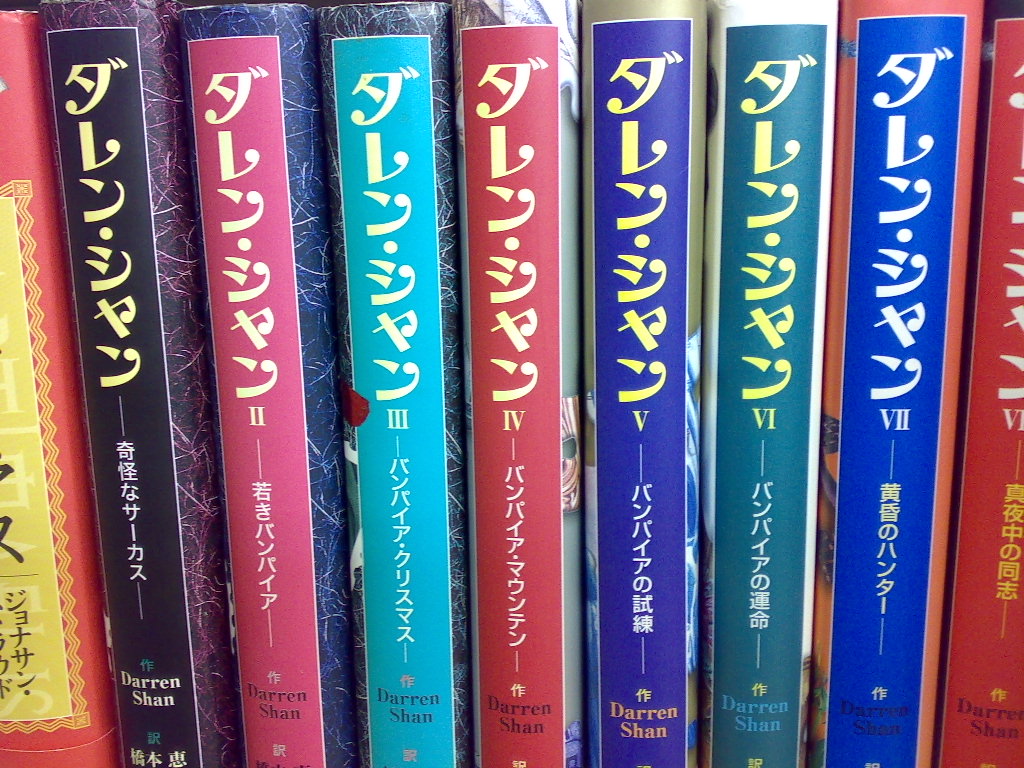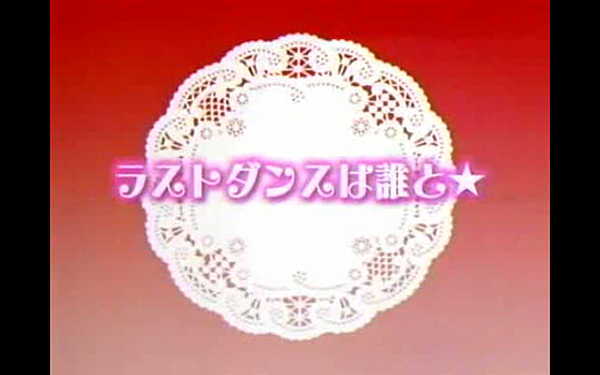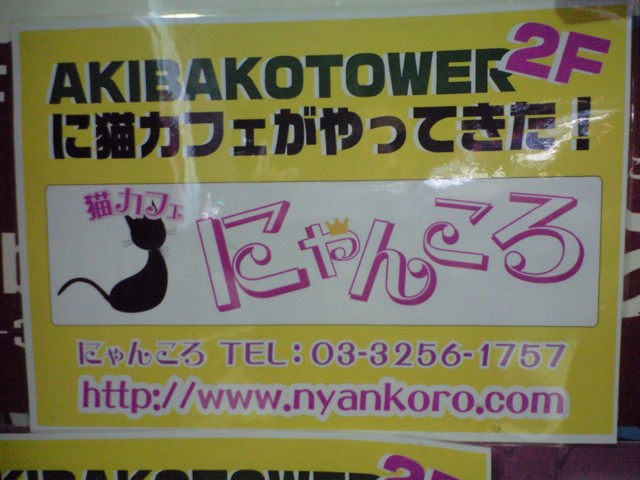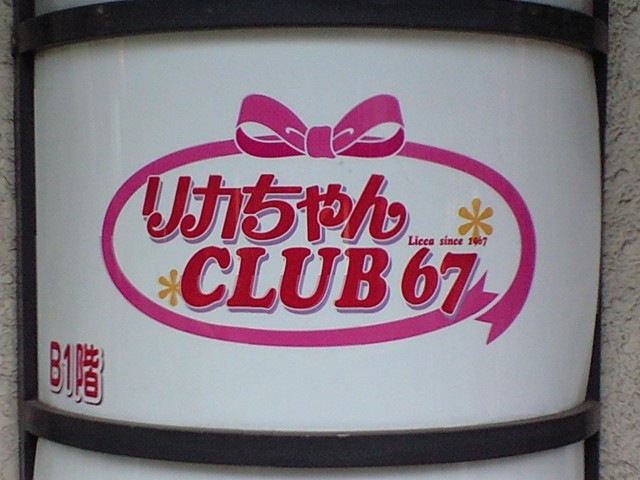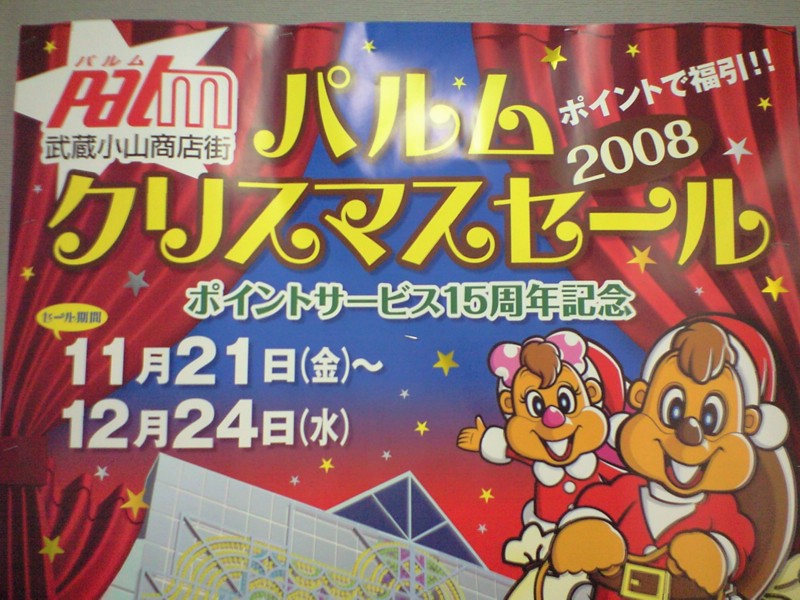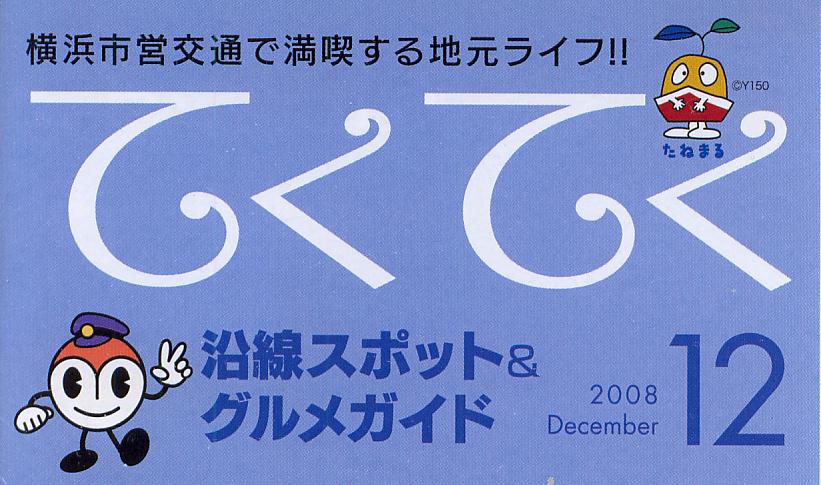
とてもキュートなフォントなので購入しました。
楽しい画像が作れそうです!
旅行案内リーフレット  さとうゆたか  2010年1月13日(水) 17:18
ハワイには行ったことがありません…。
コミックスの広告  さとうゆたか  2009年12月21日(月) 15:06
書名:星守る犬
著者:村上たかし
発行:双葉社
本の書名部分  さとうゆたか  2009年12月2日(水) 11:00
書名:親子で作る はじめてのスイーツ
著者:りぼん特別編集
監修:青木定治
発行:集英社
応募カード  イワオ ハウス  2009年11月16日(月) 16:40  HP Mail
季節ごとに出ているスーパーでの
応募カード、「えれがんとW9」よりも
太くしてあるようです。
クッキリハッキリと、この書体の可愛らしさが出てますね。
フォントワークスから販売されている物には、このぐらい太いのもありますよ。
無料の清音フォントですから、全ての文字が表示される訳ではありません。
そのサンプル表示枠の右下に「フォントをインストール」という文字が見えませんか。
そこをクリックすると、フォントがインストールされます(MacのOSが10.3以上なら)。
Emikoさんは、フォントをインストールされるのは初めてですか?
それなら、当サイト内のフォントの知識あれこれ「はじめてのフォント」ページも、ご覧になってください。
また、えれがんと無料お試し版は「えれがんと清音」ということで、濁音・半濁音・拗音促音などは、含まれておりません。
商品版には、それらの文字も含まれております。
かな書体ですから、どちらにも漢字は含まれておりません。
よろしくお願いいたします。
Emiko  2009年10月5日(月) 18:07 [修正]
さとうさん、
いつも素早いお返事ありがとうございます。
『ファイルを開く(またはダブルクリック)と、FontBookアプリのサンプル表示になり、フォントの一部が見える筈です。』
との事ですが、ファイルをダブルクリックして、FontBookアプリのサンプル表示になった時にそのサンプルが文字化けしてしまっているのです。
なので、フォントをインストールしても文字化けしたままです。
この間、他のところでフォントをインストールしました。その時は文字化けせずにインストールで来ました。(しかし、どうにそのインストールした文字も使うのか良くわからず、あまり使えていません。インストールしたフォントは普段通りローマ字打ちは出来ないのでしょうか?)
私のパソコンが悪いのでしょうか?
スグにでも「えれがんとw9」を使いたいのですが、どうしたら良いのでしょうか?
「えれがんとw9」を買う事を考えてはいるのですが、同じ問題が起こり使えないのだと残念なので、心配しています。
宜しくお願い致します。
さとうゆたか  2009年10月5日(月) 21:39 [修正]
Emikoさんのいう「文字化け」って、どういうものですか?
ひらがなもカタカナも1文字も見えませんか?
「はじめてのフォント」ページをご覧になって、Fontsフォルダへのコピーとかも試してください。
「インストールした文字をどう使うのか良くわからず」
インストール後は、お使いのアプリケーションソフトで、フォントメニューから使用したいフォントを選ぶのです……。
「普段通りローマ字打ち」?????
かな文字入力もローマ字入力もできる日本語フォントです。
商品版も無料お試し版も、使える文字数以外は同じように作られています。
Emikoさんのやり方で、無料お試し版が使えないのでしたら、商品版を購入しても使えない可能性大です。
たぶん、どこかで何か勘違いしているような気がします。
「はじめてのフォント」ページに記されている事を、試したり理解できるようになっていただきたいと思います。
無料の「えれがんと清音」Mac用フォントは、2000年から毎日数十人の方にダウンロードされており、フォントファイルには特に問題は無いと思われます。
Emiko  2009年10月6日(火) 0:06 [修正]
はい。私も何か抜けているのではないかと思い、はじめてのフォントも何度も読み直してみました。
「えれがんと」の文字化けの様子ですが、全くひらがな、カタカナは読めません。ただ縦長の四角が並んでいるだけです。
もしかしてと思い、他のフォント「アニト、キャパニト、セプテンバー、ルイカ」をインストールしてみましたが、問題なくインストール出来ました。
なぜ「えれがんと」だけ出来ないのか疑問です。
製品版のCD-R版を使っても同じ事でしょうか?
CD-Rの方は1フォント(えれがんとw9)だけでは売っていないですか?
さとうゆたか  2009年10月6日(火) 6:33 [修正]
まずやってみて欲しい事(すでにやったことならゴメンナサイ)
●これまでのえれがんとフォントと圧縮ファイルなどを全部捨てて、もう一度えれがんと無料板をダウンロードし、インストールする。
●インストール方法は問いませんが、W3〜W9の4つ全部インストールしてください。
FontBookのサンプル表示設定が漢字や英数字だけになっていたら、えれがんとはうまく表示されない(かなだけのフォントなので)と思います。
FontBookのサンプル表示が文字化けしていても構わずインストールしてください。
そして何らかのソフトで実際に文字を打って(えれがんとを使って)みてください(この時点でどうなるかが、一番重要です)。
●無料のお試し版がうまくインストール出来なかったら、商品版でも同じ結果になると思います。
●CD-Rで1フォントだけ売ると、割高になるので今のところやっておりません。彩字専科に特別注文すればやってくれるかもしれませんが、お試し版がうまく使えない今の状況では、商品版を購入されても無駄になるだけです。
そういうことにならないように、お試ししてから安心して購入できるように運営しているシステムですから。
Emiko  2009年10月6日(火) 22:53 [修正]
何度も申し訳ありません。
さとうさんのアドバイス通りもう一度始めからやり直し、文字化けしたままフォントをインストールしました。やはりダメです。実際に文字を打ってみましたが、文字化けしたままです。
なので、父の使っているWindowsでインストールしてみました。
Windowsに慣れていないので少し悪戦苦闘しましたが、無事にインストール出来ました。
やはり私の古いMacが悪いのでしょうか?
実は近々新しいMacを購入予定だったので、それを早める事にしました。
その新しいパソコンが来たらまた、トライしてみようと思います。
何度も私の訳分からない質問に付き合って下さり、ありがとうございました。本当に嬉しかったです。
さとうゆたか  2009年10月6日(火) 23:10 [修正]
Emikoさんが使っているMacのOSは何ですか?
もしOS9以下でしたら、フォントと一緒に入っている「必ず読んでください(清音版)」に記してある通り、システムフォルダにフォントを入れてください。
もしかしたら漢字Talk7.5以下なのでしょうか?
また、Macでえれがんとを使うソフトは何でしょう?
私は20年以上のMacユーザですから「Macの購入をやめた」なんて言われると、ちょっと哀しいですけどね。
最新のMacでも「えれがんと」は使える筈ですよ。
Mac用えれがんと無料版は、これまで一万数千人にダウンロードされていますが、使えないなんて誰からも報告されておりませんから。
お世話になりました。  Emiko  2009年10月7日(水) 17:10 [修正]
本日新しいMacbook Proが届きましたので、試してみたらインストールできました。
なので商品版ファミリーパックを購入させて頂きました。
私が昨日まで使っていたMacはMac OS X version10.5.7でした。
なぜインストールができなかったのかは今も不明ですが、今はどうしても使いたかった「えれがんと」フォントが使えるのでとてもうれしいです。
ありがとうございました。
さとうゆたか  2009年10月7日(水) 22:43 [修正]
商品版のご購入ありがとうございました。
Emikoさんは「Macの購入をやめた」なんて発言してませんよね。
プライベートなこと(葬儀関係)で、ちょっとアタフタしていて、
「早める事にしました」という文章を「やめる事にしました」と読んでしまい申し訳ありませんでした…。
えれがんとフォントが使えるようになって良かったですね。
フォント作者という立場からも、Macユーザという立場からしてもウレシイです。
秋葉原にて  Mighty  2009年9月17日(木) 21:16
パチンコ店の前にて。
さとうゆたか  2009年9月18日(金) 6:05 [修正]
Mightyさん いつも投稿ありがとう!
郵便局でランドセル  さとうゆたか  2009年9月9日(水) 17:08
ひさしぶりに行った郵便局でみつけました。
劇場名  さとうゆたか  2009年5月8日(金) 16:45
1010と書いて「せんじゅ」と読むらしい。
いま気づいたが「タ」の文字と「音引き」には少し手が加えられている。
以前見かけたものですね  Mighty  2009年7月19日(日) 11:10 [修正]
引越しお疲れ様です。
活動も、北は北千住から南は南千住まで…(コラー—^^;)
(もちろん、そんなに狭くはありません。北千住のつかみネタでした)
さとうゆたか  2009年7月19日(日) 21:41 [修正]
あ、芝居のポスターに使われているのを前に投稿していただいてますね。